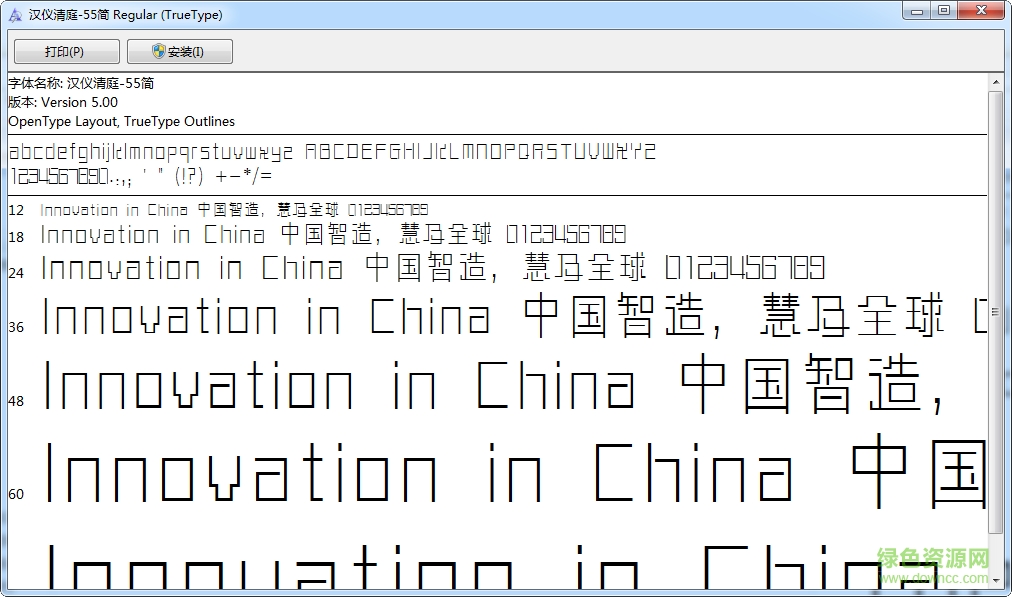
漢儀清庭體簡(jiǎn)體字體是中文字體庫(kù)中的一款字體,字體看起來(lái)像是爬行出來(lái)的,每一筆的拐角都是90度,適合應(yīng)用于廣告設(shè)計(jì)、名片設(shè)計(jì)、包裝印刷、產(chǎn)品設(shè)計(jì)等應(yīng)用。歡迎來(lái)綠色資源網(wǎng)下載。